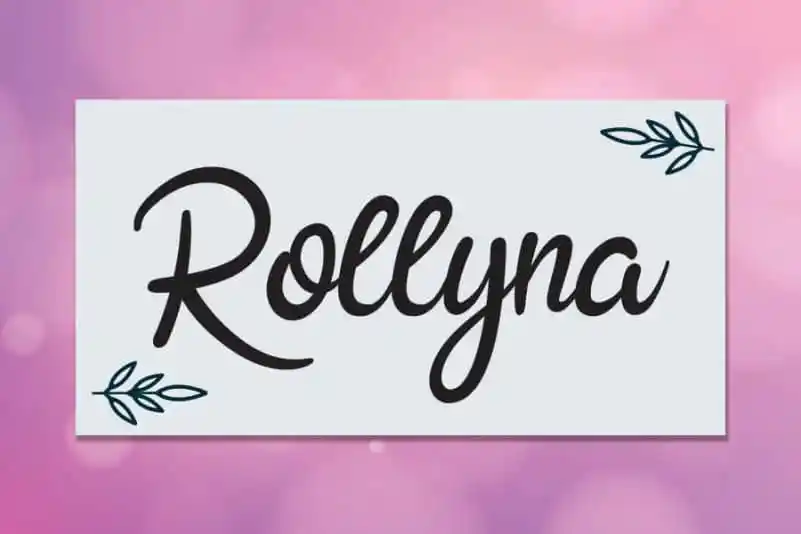
Rollyna Script Font – Download Grátis
Rollyna Script Font é uma elegante fonte escrita à mão que transmite um toque delicado. Conhecida por seu estilo distintivo e eterno, ela é perfeita para projetos pessoais e profissionais. Essa fonte não apenas encanta com sua personalidade única, mas também lhe dá a liberdade de criar designs incrivelmente únicos e impressionantes. É ideal tanto para trabalhos digitais quanto para impressão em papel, oferecendo um toque especial e único que se destaca no mundo das criações visuais. Seja você designer gráfico ou escritor, Rollyna Script Font é uma escolha perfeita para aqueles que valorizam a personalização e o detalhe em seus projetos. Descubra por si mesmo o poder de transformar sua ideia única em arte impressa com esta fonte à mão.